限動如何換字體 | ZiZi 教學
instagram內建中文字體較少(基本上中文只會顯示黑體),今天教你如何美化限動,讓限動有用更多字體!
秘密武器:ZiZi 全能限動改造王
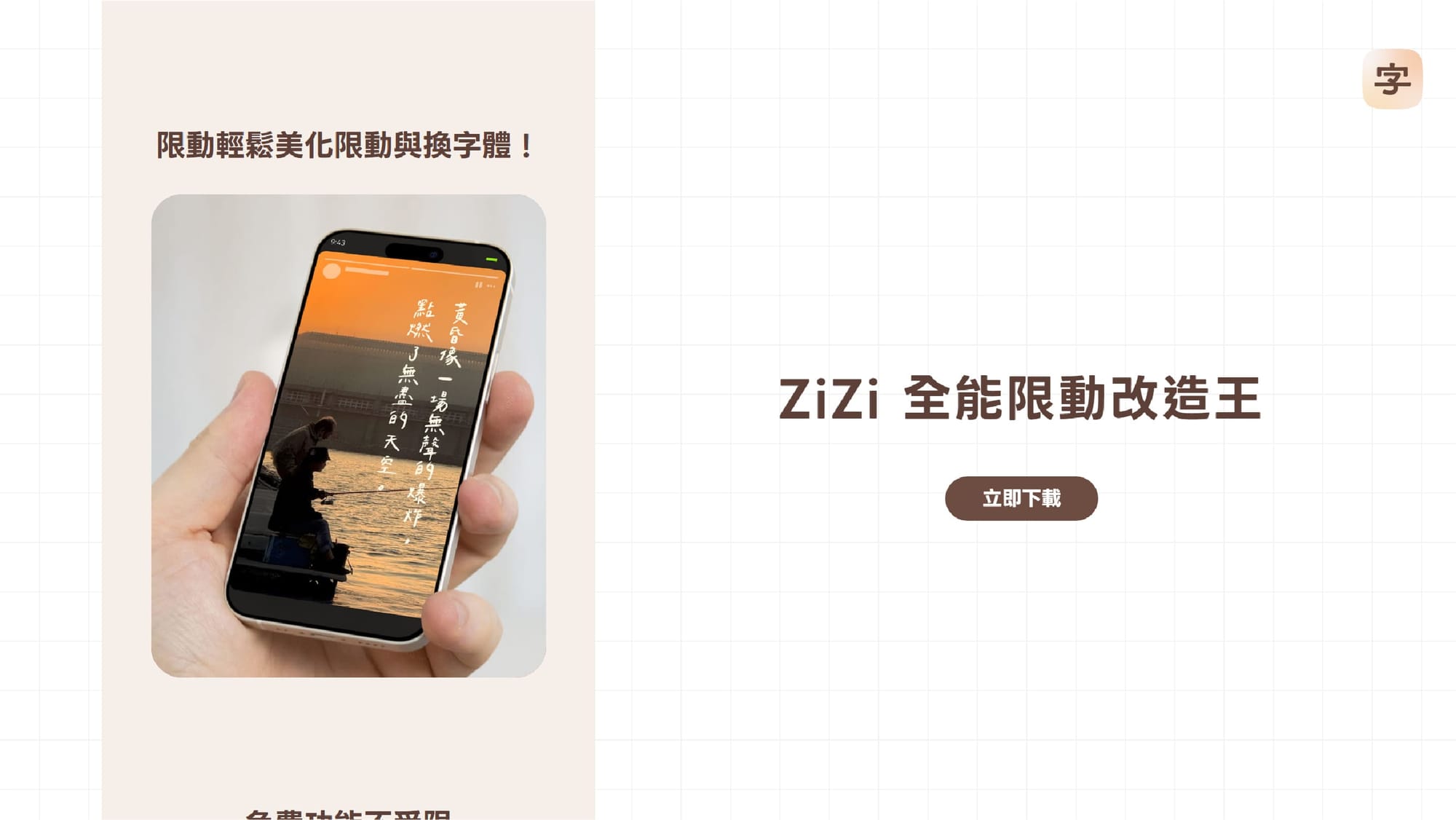
ZiZi 是由 TwinType 打造的限動排版工具,支援 Android 與 iOS,內建 20 多款字體,也可自行匯入字體,或是透過 TwinType Cloud 小額訂閱解鎖更多優質字體。
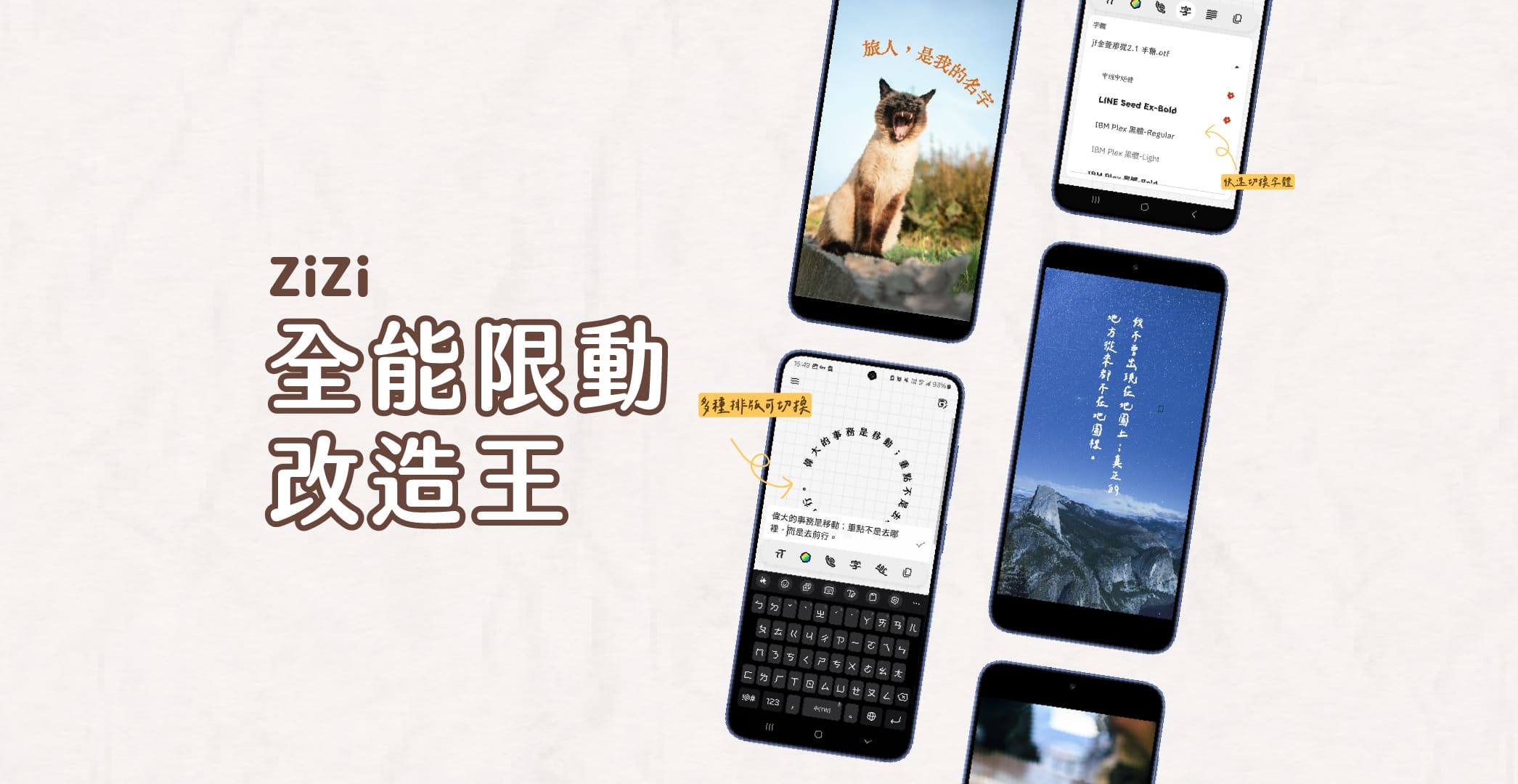
使用教學
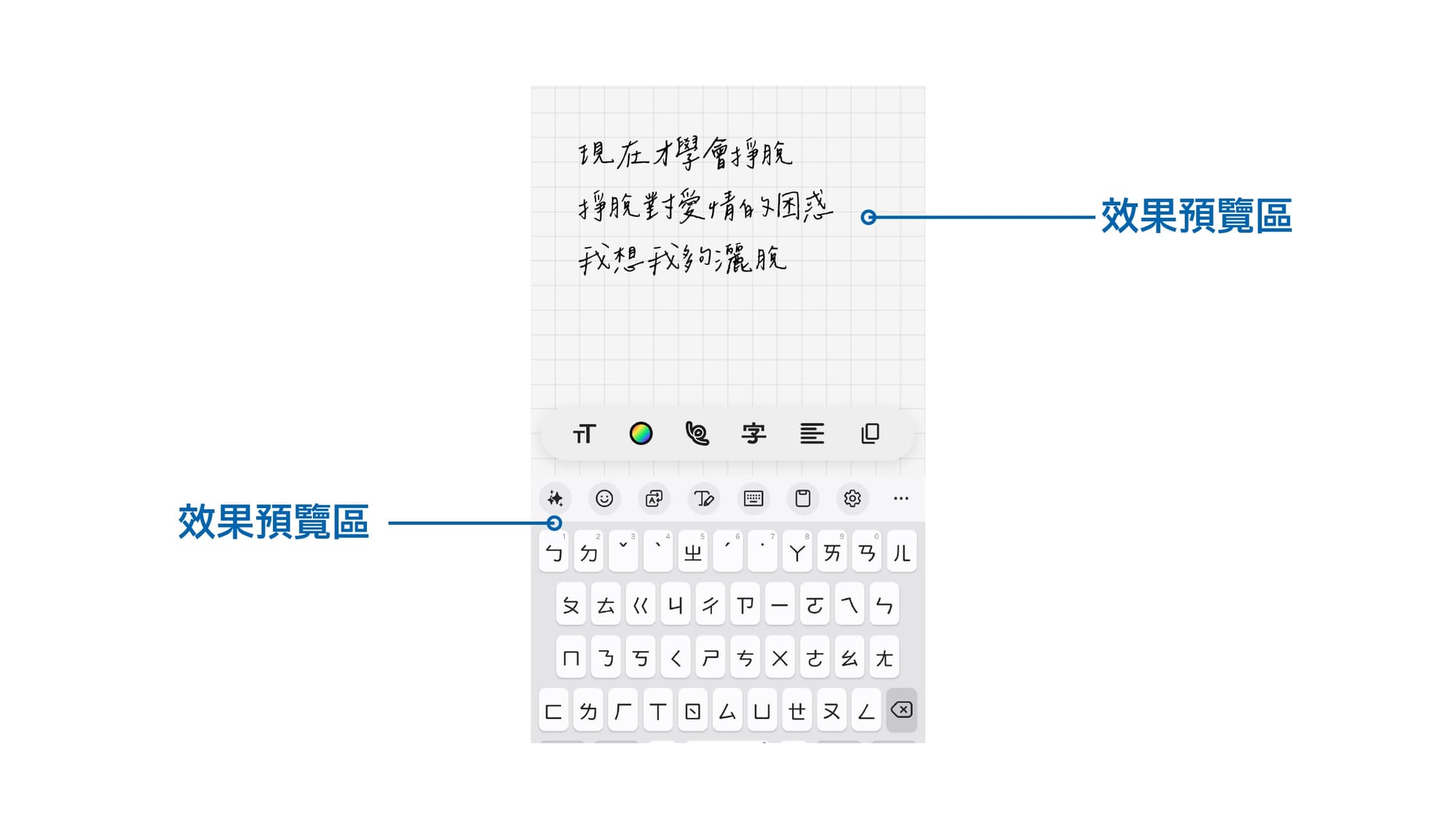
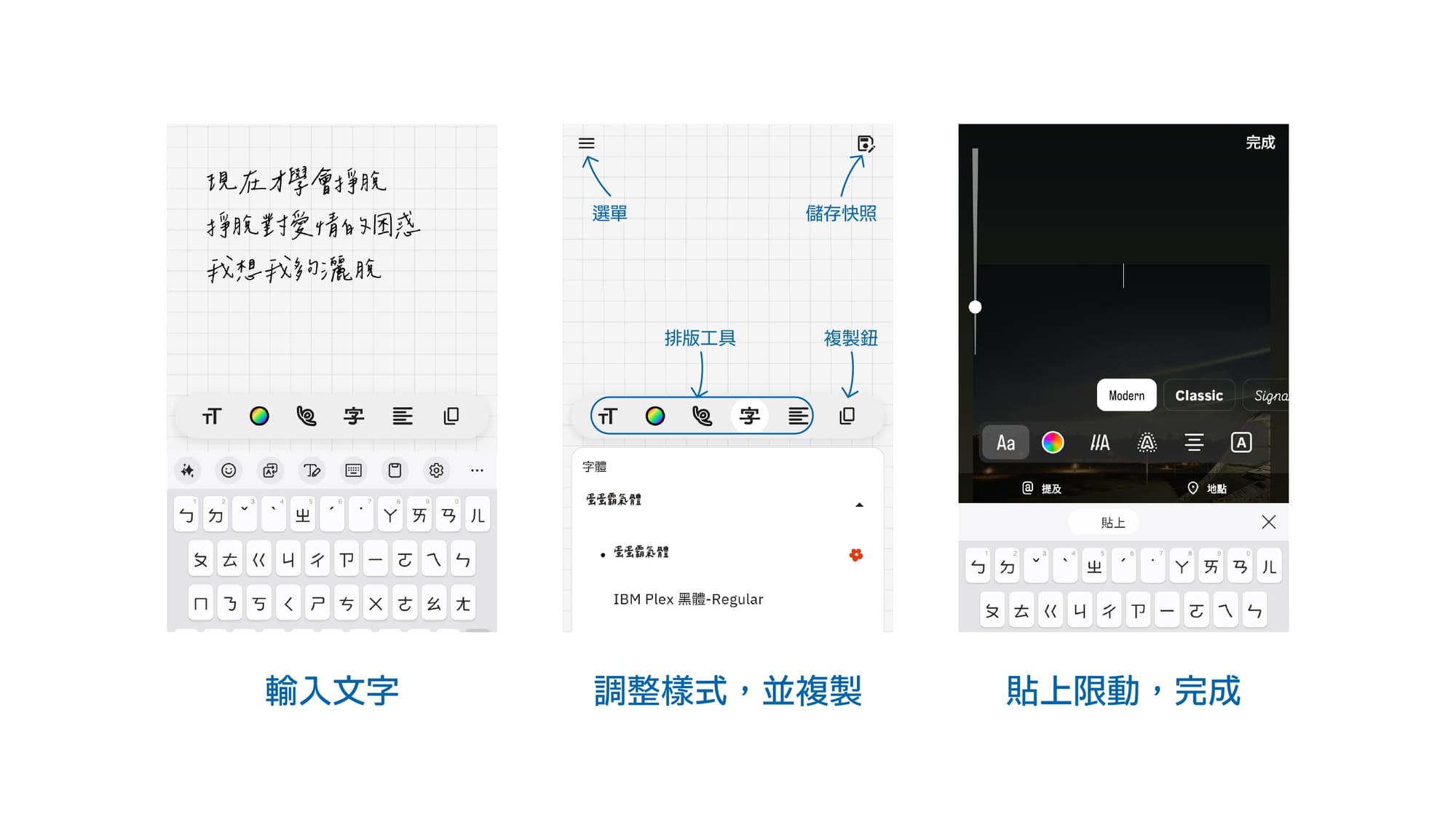
- 開啟後,映入眼簾的是編輯區,可以接文本書寫於此
- 下方工具列,可調整文字樣式,會及時根據排版調整顯示樣式。
- 最後一步,只要點選「複製」按鈕,再到 instagram 限動文字區,「貼上」,就完成啦!
ZiZi 文字編輯工具列介紹
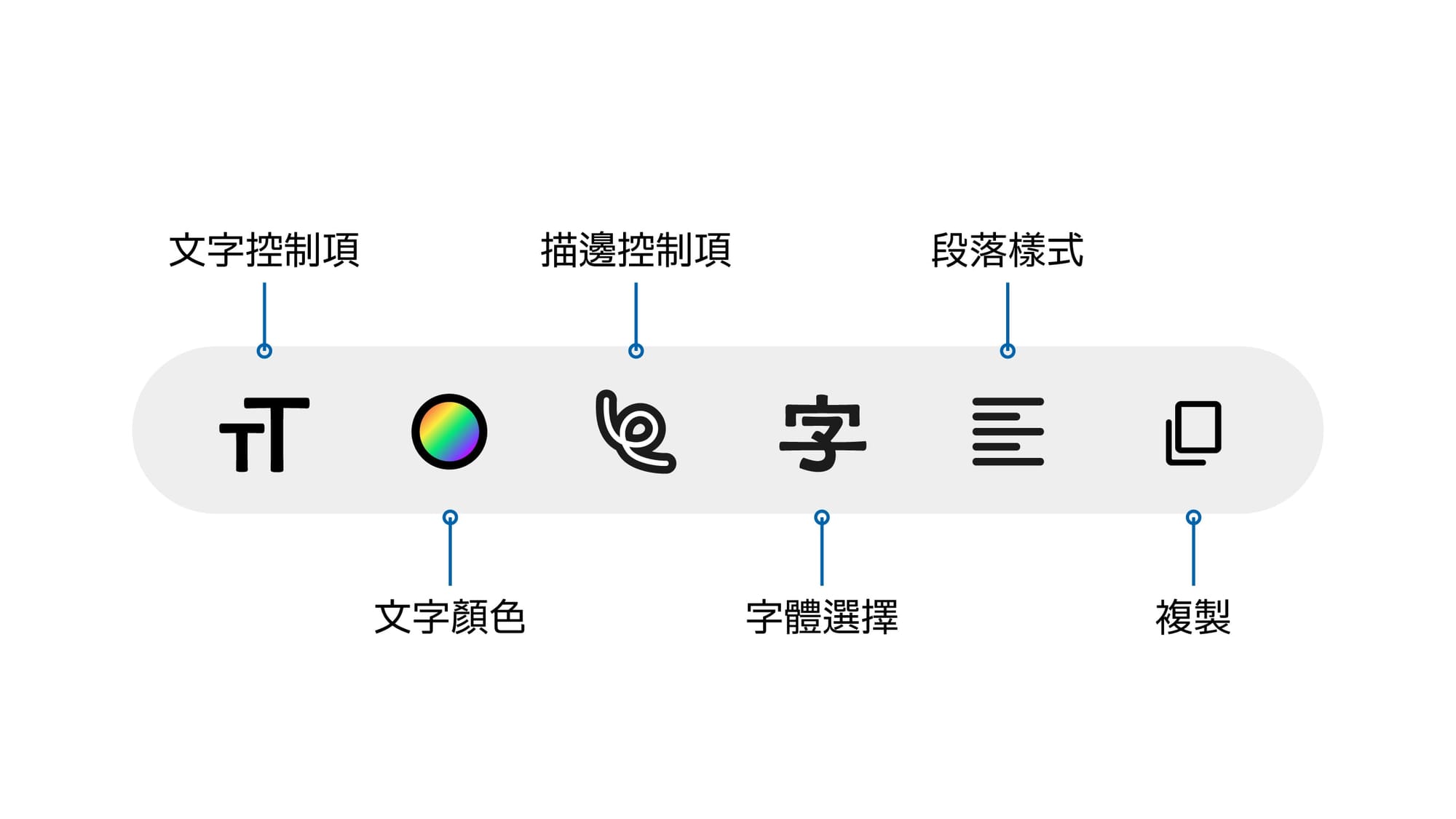
由左至右分別為
- 文字控制項
- 文字顏色
- 描邊控制項
- 字體選擇列表
- 段落樣式
- 複製按鈕
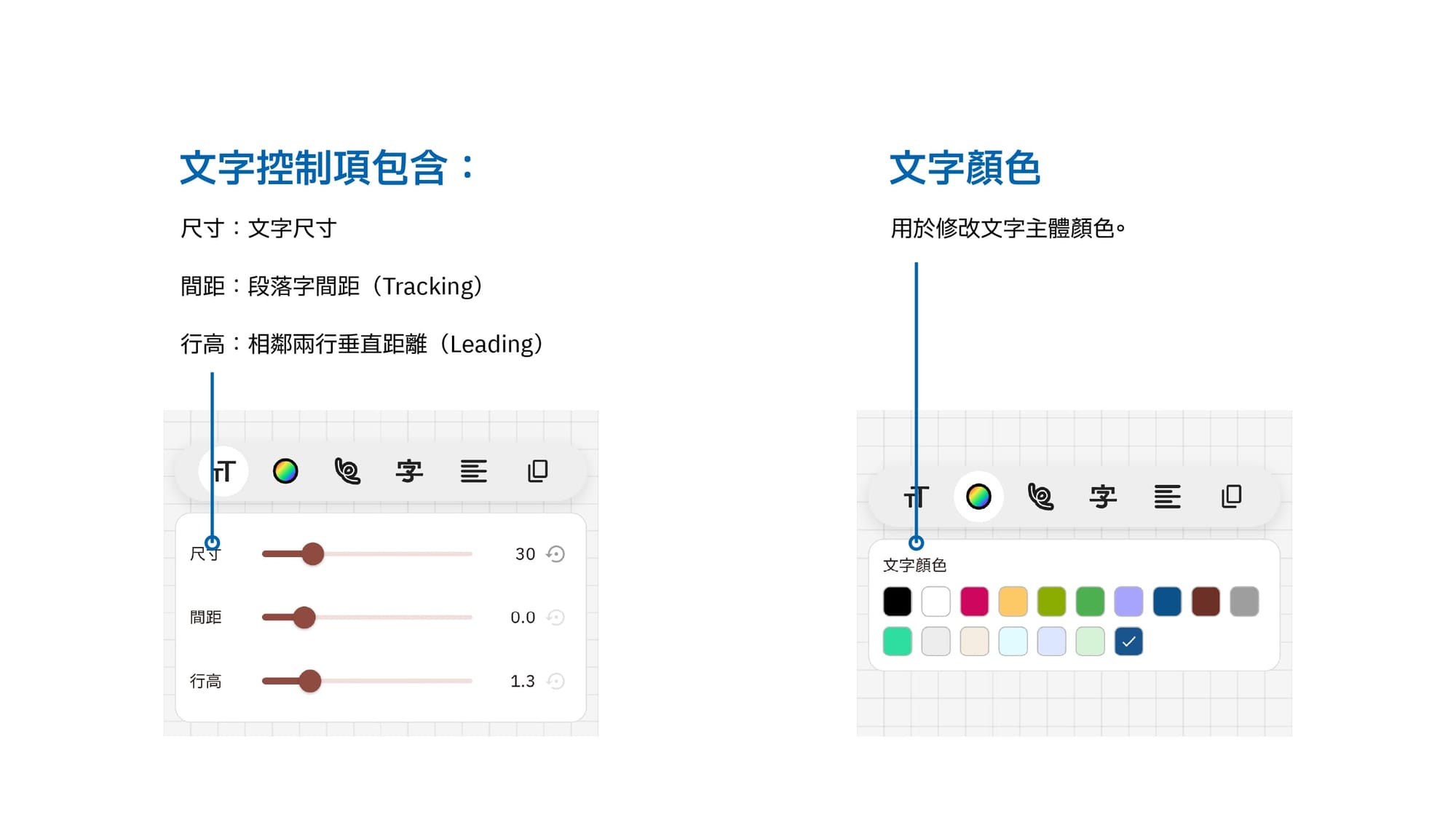
文字控制項,可以調整文字尺寸、間距與行高。
小提示:如果文字數較多,可以優先選用裝飾性較少的字體,適當提高「行高」有助於閱讀喔!
文字顏色
文字顏色,有提供多種預設選項,當然也可以自己調整,請填選最末端「+」號按鈕即可自己調配!
小提示:淺色文字,背景會自動轉為深色,不影響實際輸出的樣式喔!
描邊控制項
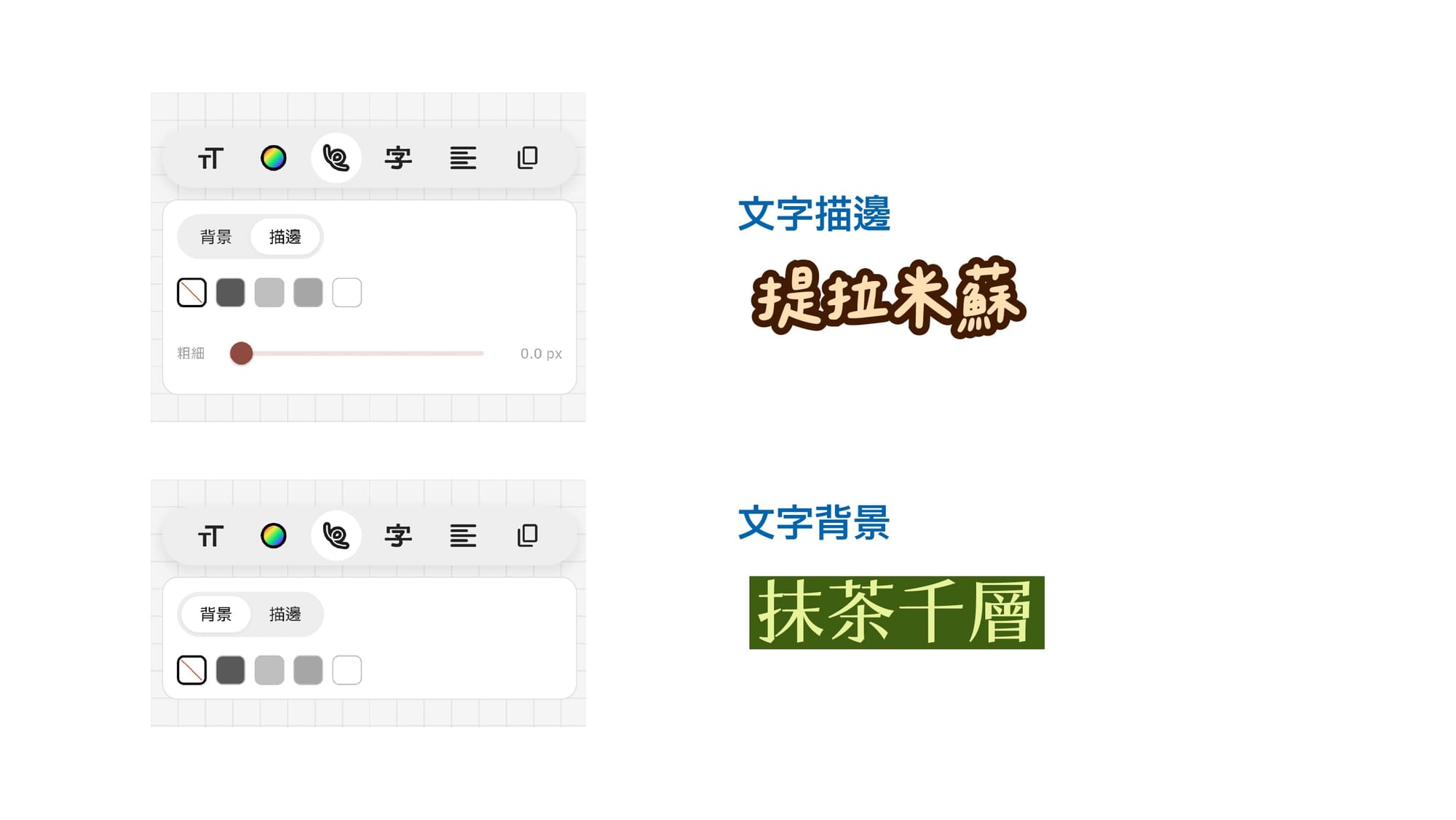
斯斯有兩種,描邊也有。
- 「描邊」會將文字沿文字符輪廓加上邊框,如上圖「提拉米蘇」字樣。
- 「背景」會將文字框視為整體,在背景加上矩形色塊
不論何種描邊,皆可任意更改顏色,但不可同時存在!
段落樣式
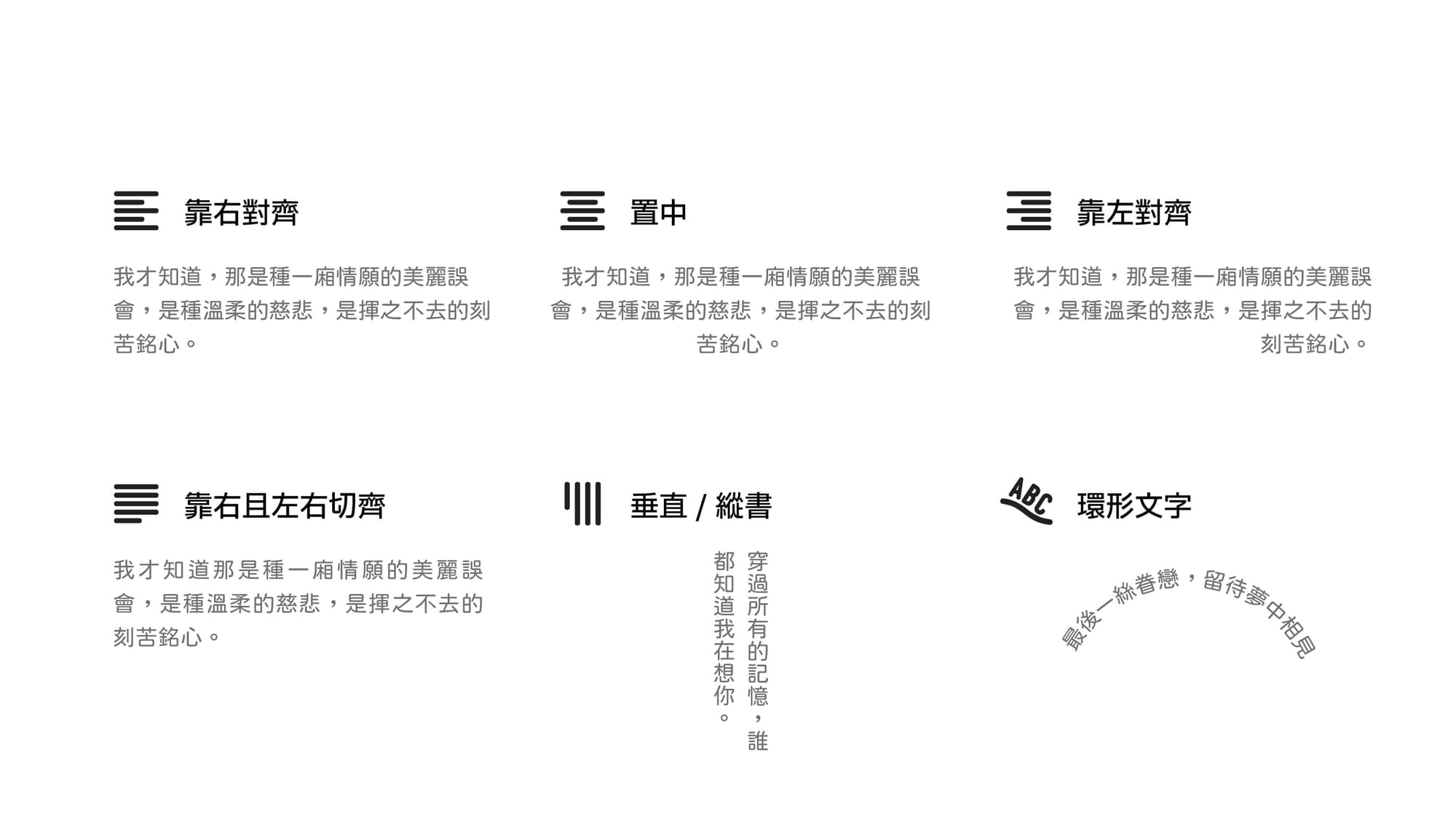
斯斯有兩種,段落樣式有六種。
- 「靠右對齊」文字靠右邊切齊。
- 「置中」置中對齊。
- 「靠左對齊」文字靠左邊切齊。
- 「靠右且左右切齊」文字靠右邊切齊,但左側同時也會切齊,程式會自動運算擠壓或是加大字元間距(Spacing)。
- 「垂直 / 縱書」垂直文字樣式,上下皆會自動切齊。
- 「環形文字」文字沿著圓形排列,啟用該選項後可以回到「文字控制項」選擇角度與方向。
小提示:除了「環形文字」外,其餘段落樣式,皆已啟用「避頭尾」。
字體選擇
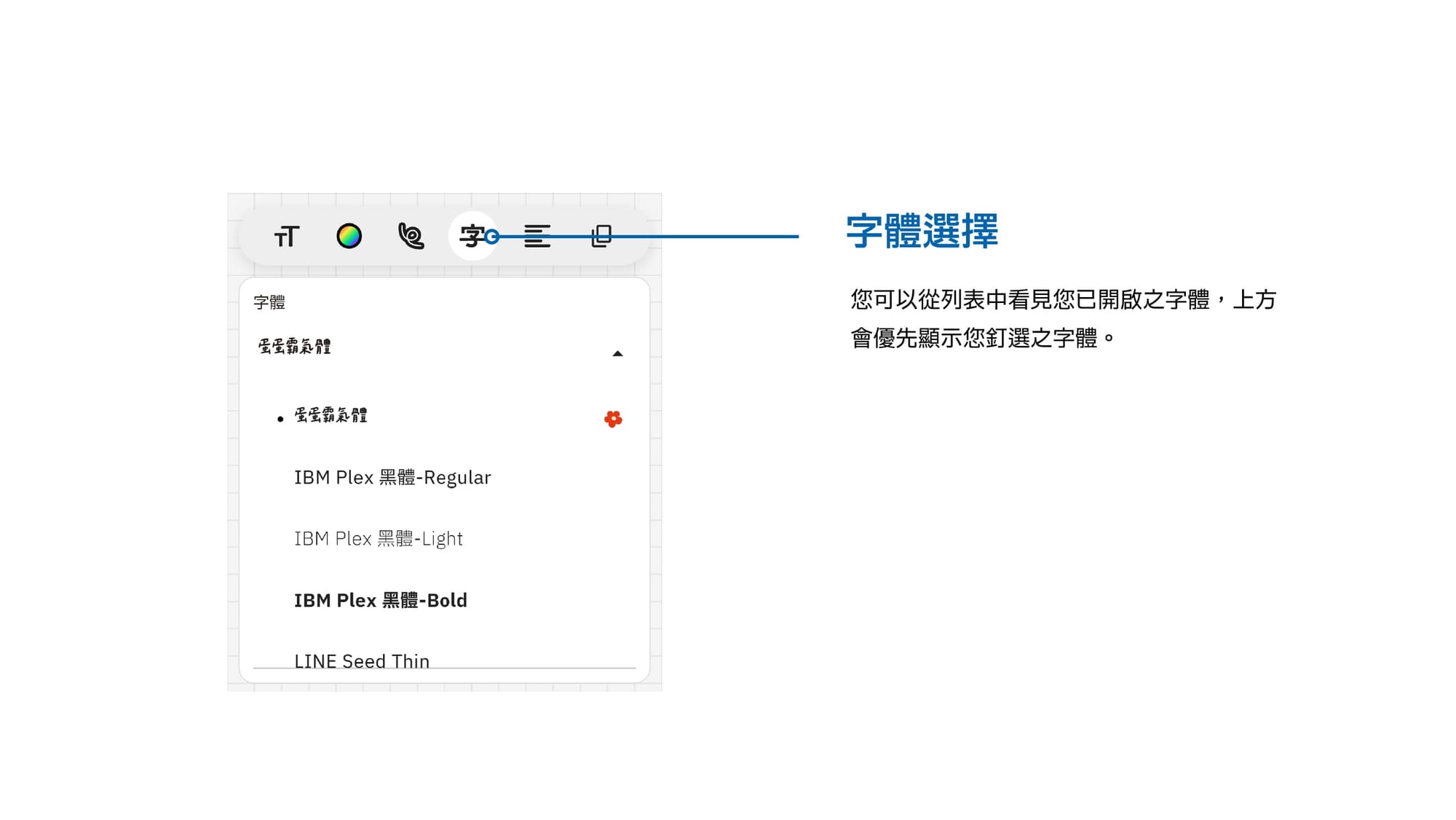
斯斯有兩種,內建字體超多種。ZiZi 內建 20 多款可商用與開源字型,絕大部分可以透過雲端調用,不必在手機上安裝一大堆字體文件(容量救星✌🏼)。
詳細字體列表,可點前往ZiZi官網點選「預載字體」查看,或開啟APP查看。在APP中你只需要點選工具列的「字」圖示,即可任意切換字體風格。最上方會是你所訂選的字體。
儲存草稿:快照功能
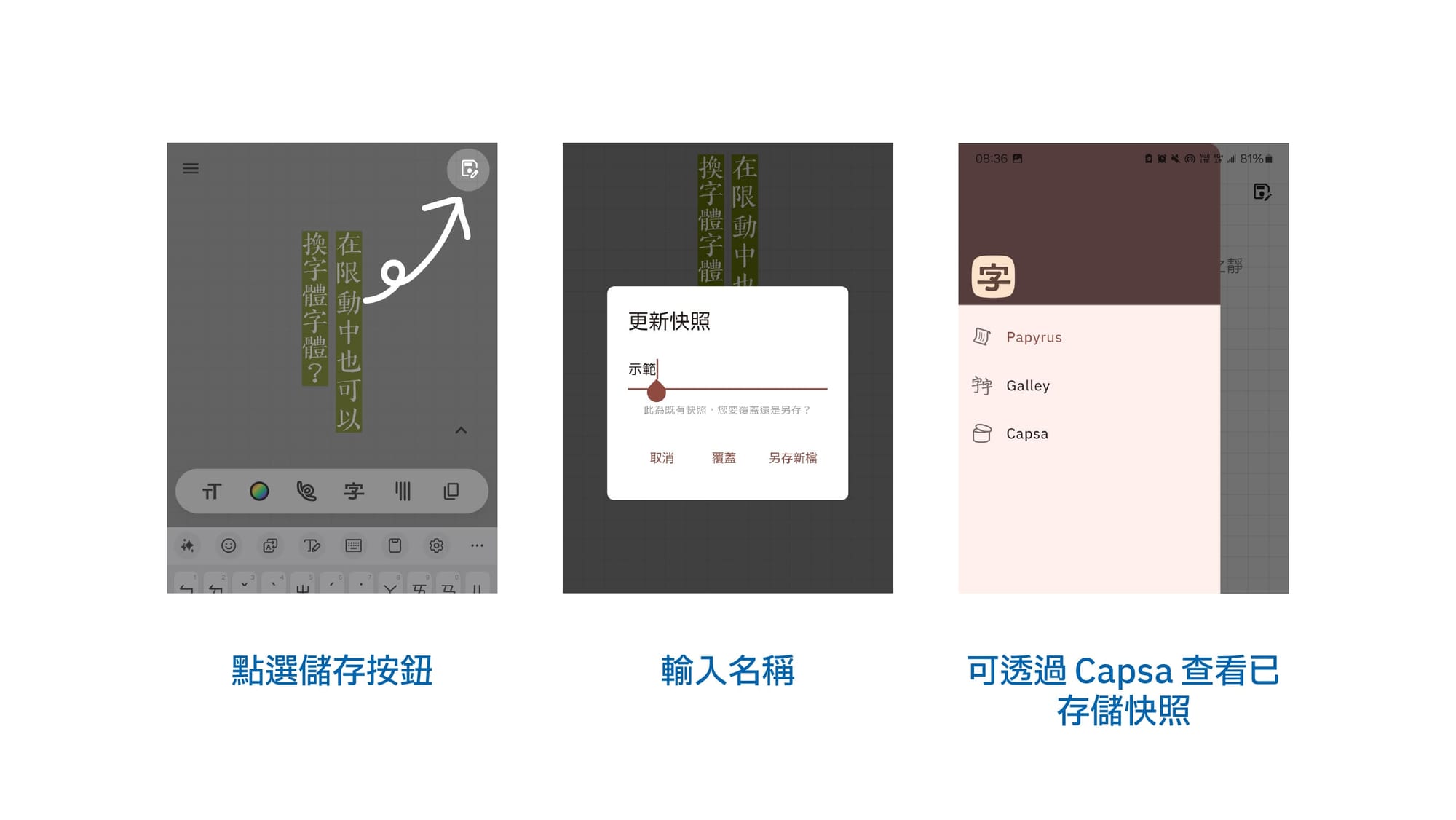
編輯到一半,需要先離開,或是想存著下次複用?沒問題,可以點選「快照」圖示即可儲存。
之後可以開啟選單,點選「Capsa」即可查看已經儲存的快照。
匯入字體
開啟選單,點選「Galley」可進入字體列表,這會顯示當前可用之字體,上方有分類可查看。
可透過「小花」圖示,釘選字體至編輯介面的字體列表中,「眼睛」圖是可以選擇是否顯示在列編輯介面的列表中。
小提示:大多數預設字體皆為雲端掉用,您無法刪除,但可以隱藏在編輯介面(Papyrus)的列表中。其中有兩款預設字體,「jf-粉圓體」、「霞鶩文楷TC」為安裝置至本地中,作為備案,當您處於無網路環境下,將會自動自動退回(Fallback )此字體。
小額訂閱字體
本次文中,多張片畫面使用〈蛋蛋霸氣體〉,這是一款豪放搶眼,真誠不做作的手寫字體!
由圖文作家——蛋頭親筆繪製,且加入多個 emoji,讓你用字體表達喜怒哀樂。非常適合用在社群中,而且內含 80 多個彩色 emoji!